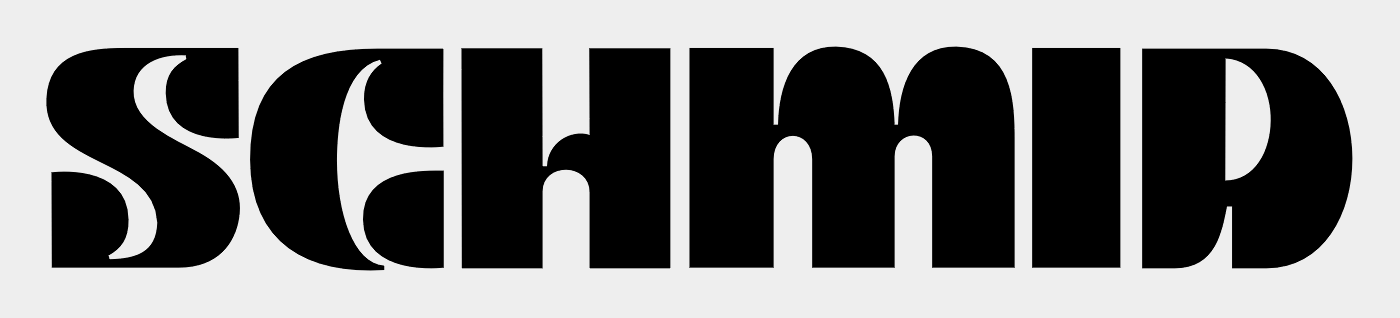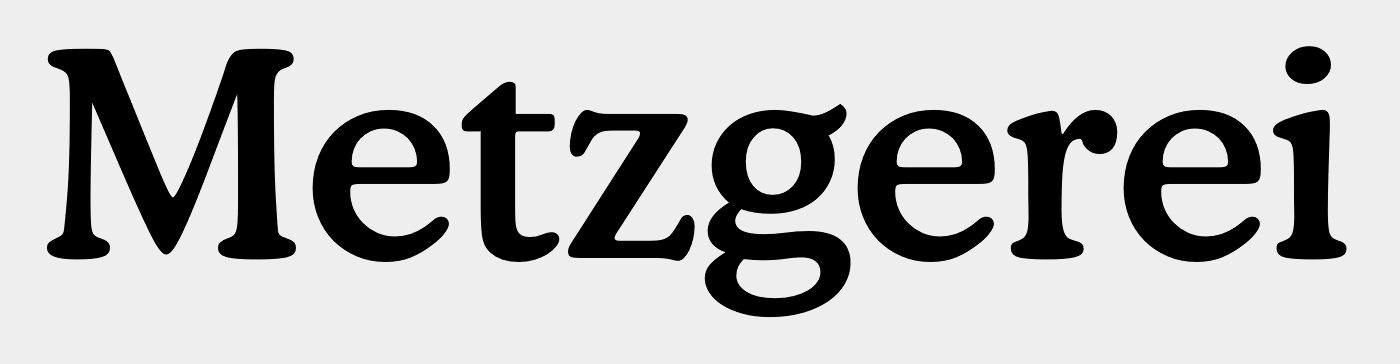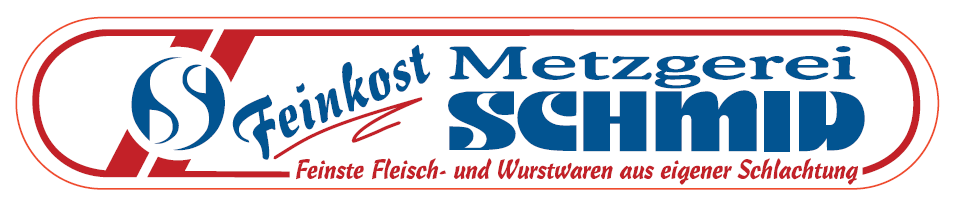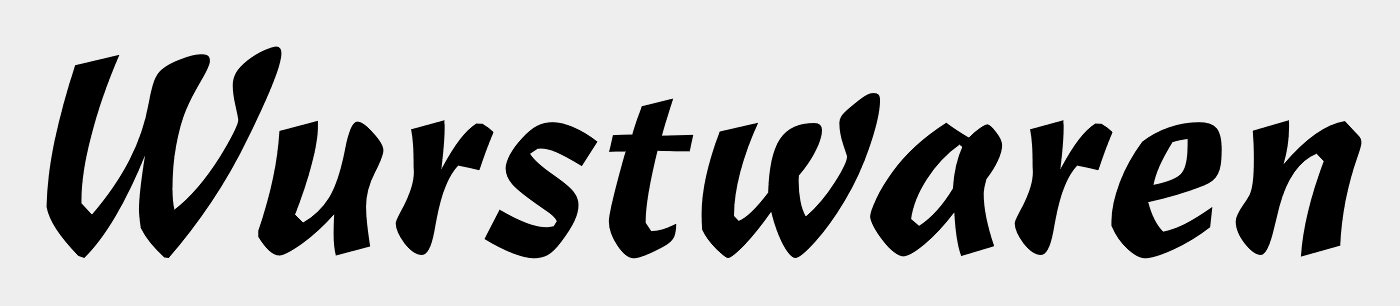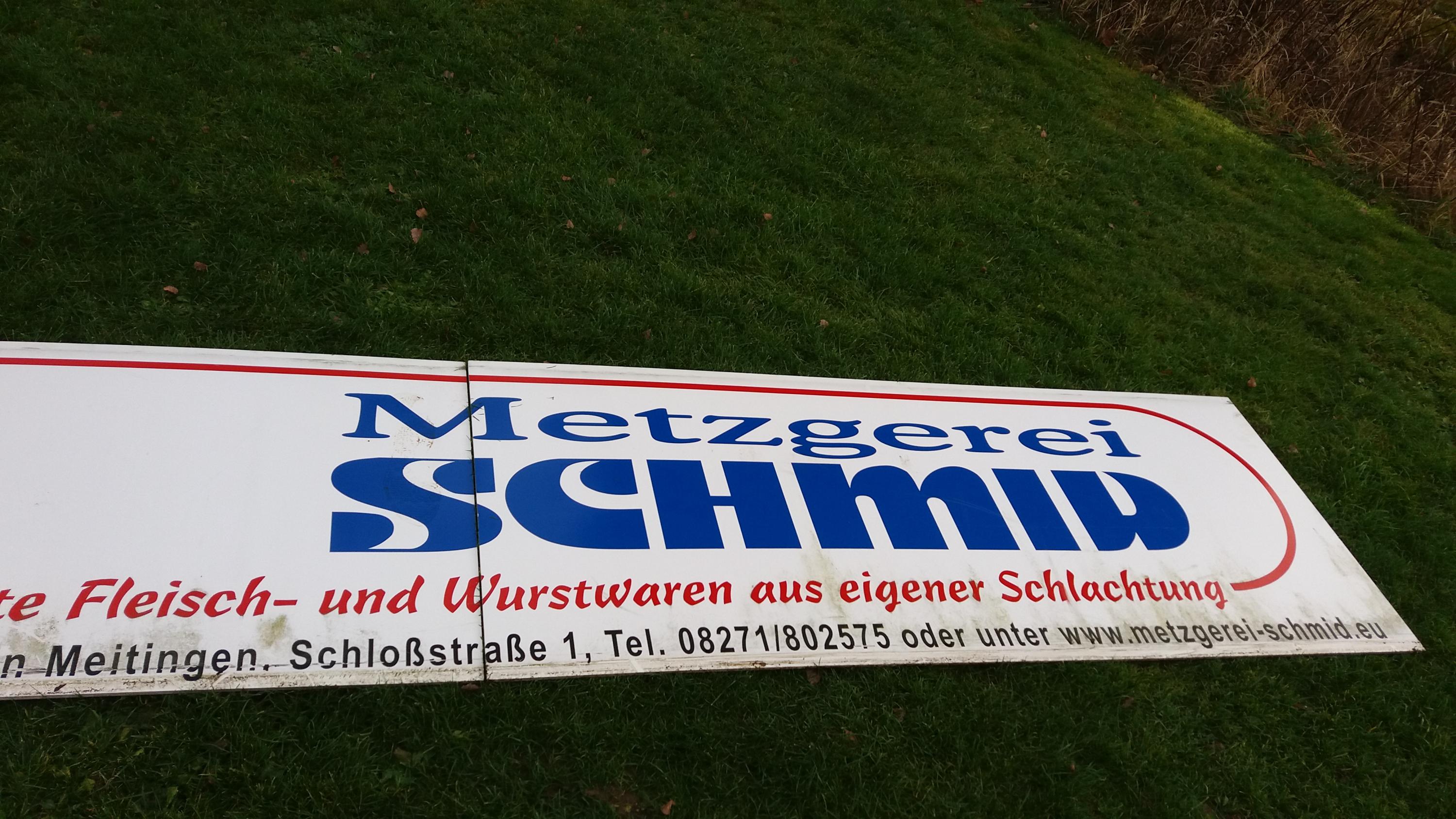
Suche Schriftnamen (Metzgerei)
Hallo, ich würde diese Schrift suchen um eine neue Bandenwerbung zu erstellen, da die das alte Schild defekt ist.
Metzgerei Schmid, vielleicht auch noch die darunter
SCHMID ist aus der Kare Regular (falls die dieses C hat) oder Motter Ombra, das H wurde entweder konstruiert oder aus einer anderen Schrift entnommen.
Motter Ombra:
vielen Dank, kannst du noch die darunter stehende Schrift, (Wurstwaren) beurteilen?
auf 200 % Breite gestreckt.
Falls du das Metzgerei-Banner meinst: Das hab ich nur schnell gegoogelt. Ist von der Wirtschaftsvereinigung Buttenwiesen e.V., vielleicht haben die außer diesem png auch noch Vektordaten vom Metzger bekommen?
Ich finde, das falsche H sieht wesentlich besser und stimmiger aus als das originale aus der Motter. Jenes tut wirklich weh.
Das ohne Not oben abgesäbelte D (V? U?) auch. Hier täte ein (behutsames) Redesign wirklich gut und würde vom Kunden bestimmt auch akzeptiert werden.